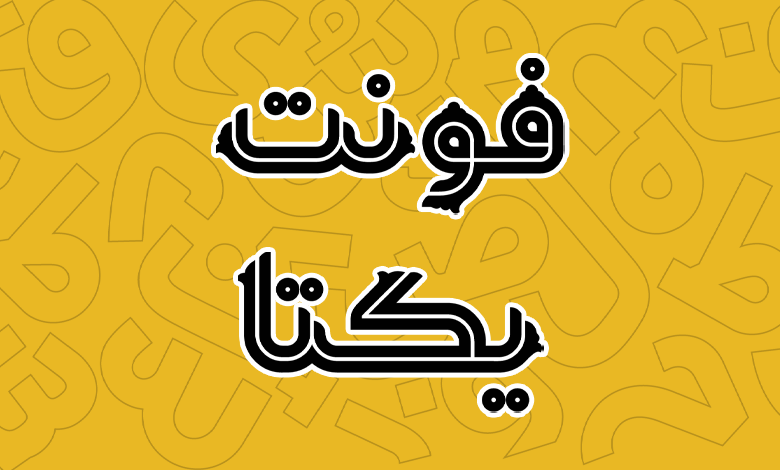
فونت یکتا (Yekta)
فونت یکتا (Yekta) فونتی نمایشی و تزئینی است که ساختاری کاملا هندسی دارد و از آن میتوان برای موضوعات فرهنگی یا تبلیغات محیطی استفاده کرد. این فونت با الهام گرفتن از خطوط اسلیمی ساخته شده است که توسط وحید یعقوبلو طراحی و امین عابدی توسعه نرمافزاری آن را انجام داده است.
در فونت یکتا از سبک طراحی اینلاین (in-line) استفاده شده است که ساختار حروف به صورت دوخطی هستند و در یکی از وزنها از زوائد تزئینی استفاده شده است. همین زوائد این فونت را به فونت اسلیمی ایرانی نزدیکتر کرده و باعث شده که در طراحیهایی که برای کارهای گرافیکی و فرهنگی انجام خواهید داد نشان از اصالت و ایرانی بودن دیده شود.
در ادامه این نوشته از سایت فونتچی به نقد و بررسی کامل فونت یکتا خواهیم پرداخت؛ فونتی که ضمن داشتن ساختاری هندسی، از نقاط گرد و حروف جایگزین متعددی پشتیبانی میکند.
معرفی و بررسی فونت یکتا (Yekta)
قلم یکتا دارای تزئیناتی است که تداعی کنندهی نقوش اسلیمی است؛ همین باعث شده که با وجود هندسی بودن حال و هوای کاملا ایرانی داشته و مناسب موضوعات فرهنگی باشد. با دیدن این فونت ناخودآگاه به یاد نقوش تاریخی و اسلیمی در شهرهای تاریخی ایران همچون اصفهان و شیراز خواهید افتاد که اگر خاطرات سفر به آنها را داشته باشید، در ذهن شما تداعی خواهند شد.
استایل و وزن فونت یکتا
استایل کلی فونت یکتا بر اساس خطوط اینلاین طراحی شده است. از همینرو خبری از وزن فونتهای رایج همچون نازک تا ضخیم در این فونت نیست و مشخصه این فونت از نظر تنوع وزنی با دو نام Yekta و Yekta-S شناخته میشود.
در وزن یکتا که نسخه معمولی و اولیه آن است شاهد استفاده از زوائد تزئینی در بخشهای مختلف حروف خصوصا شکستگیها، ابتدا و انتها، منحنیها و نواحی نزدیک به چشمیها هستیم. در حالی که در فونت Yekta-S این زوائد بهطور کلی حذف شده و همان ساختار اینلاین فونت باقی مانده است.
از همین جهت میتوانید از این دو سبک فونت یکتا برای طراحی استفاده کنید. اگر محتوای شما جنبه تزئین دارد و میخواهید که طرحی نزدیکتر به خطوط اسلیمی داشته باشید، میتوانید از این تزئینات استفاده کنید؛ در غیر اینصورت از ساختار خطی استفاده کنید.
ویژگی و امکانات فونت Yekta
فونت یکتا با وجود ساختمان و ساختاری کاملا هندسی که دارد، برای موضوعات تبلیغی، ادبی، هنری، فرهنگی و مذهبی انتخاب مناسبی است. به جرئت میتوان گفت که این فونت در بین تمامی فونتهای هندسی که الهام گرفته از طرحها و نقوش تاریخی باشند، در جایگاه اول از این نظر کاربرد قرار میگیرد و کمتر طراحانی مایل هستند تا از دیگر فونتهای هندسی در چنین حوزهای استفاده کنند.
پشتیبانی از زبان عربی و انگلیسی
فونت فارسی یکتا محدود به این زبان نبوده و از زبانهای عربی و انگلیسی نیز پشتیبانی کاملی دارد. در هر دو زبان ساختار فونت همان ساختار خطی است که میتوانید از هر دو سبک ساده اینلاین یا تزئینی دارای زوائد استفاده کنید.
در فونت یکتا عربی جدا از تایپ حروف که بر اساس رسم خط فارسی هستند، حروفی همچون «ه، ی» دارای ترکیب دو نقطه در زیر و بالا هستند که در زبان عربی به همین شیوه نوشتاری استفاده میشوند. همچنین اعراب گذاری در این فونت نیز در استاندارد بین المللی رعایت شده است.
به عنوان مثال در کلمهای مانند «حدّ» که دارای تشدید و کسره باشد، در فونت یکتا ترکیب دو اعراب «تشدید و کسره» یا تشدید با سایر اعرابهای کسره، ضمه و تنویندار، به صورت یکپارچه در زیر هم قرار میگیرند و اینطور نیست که تشدید در بالا باشد و اعرابی پایین، جدا از تشدید در زیر حروف قرار بگیرند.
پشتیبانی از اعداد در فونت یکتا هم بر اساس ساختار هر زبان است؛ مثلا در زبان عربی که اعداد «۴۵۶» دارای ظاهر متفاوتتری نسبت به زبان فارسی هستند، دارای گلیف اختصاصی خود هستند.
یکتا از زبان انگلیسی نیز با همان ساختار خطی و اینلاین تزئینی پشتیبانی میکند که میتوانید در متون دو زبانه خود از این فونت بهرهمند شوید.
دارای حروف و ترکیبات جایگزین متنوع
ویژگی دیگر فونت یکتا، پشتیبانی از حروف و ترکیبات متنوع است. در این فونت حروف و ساختارهایی همچون «ـهـ، ـه، هـ، ـی، ـن، سـ، شـ» این امکان را دارند که بتوانید آنها را در بخشهای مختلفی همچون ابتدا، میانه یا انتهای کلمات در چند حالت مختلف تایپ کنید.
این ترکیبات جایگزین در متنهایی که با هدف تبلیغات هستند یا اینکه در کارهای فرهنگی و هنری نیاز است برخی کلمات را در کانون توجه مخاطب قرار دهید کاربردی هستند و میتواند اثرگذاری از این نظر روی مخاطب داشته باشد.
این ترکیبات محدود به موارد ذکر شده نبوده و در سایر حروف مانند «ک، گ، ر، ف» و دیگر حروف نیز امکان استفاده از آنها را دارید. به کمک فایل راهنمای موجود در بسته دانلود فونت یکتا میتوانید چگونگی استفاده از هر یک از این ترکیبات را مطالعه کرده و در نرمافزارهای گرافیکی و ویرایشگر متن که چنین قابلیتی را دارند از آنها استفاده کنید.
دارای گلیف های تزئینی و نقطه گرد
همانطور که ذکر کردیم فونت یکتا دارای دو نسخه اینلاین خطی و اینلاین تزئینی است. در هر دو نسخه جدایی از اینکه کاراکترها و سمبلهای خاص پشتیبانی میشوند، از برخی از انها با توجه به ظاهری که دارند میتوانید به عنوان یک گلیف تزئینی استفاده کنید.
خصوصا برای حالتی که این کاراکترها با نسخه تزئینی فونت هماهنگتر بوده و ساختاری کاملا اسلیمی و اصیل ایرانی را به محتوا ساخته شده با این فونت در اختیار شما قرار خواهند داد. از جمله این کاراکترها میتوان به استفاده از ستاره و دیگر کاراکترهای رایج اشاره کرد.